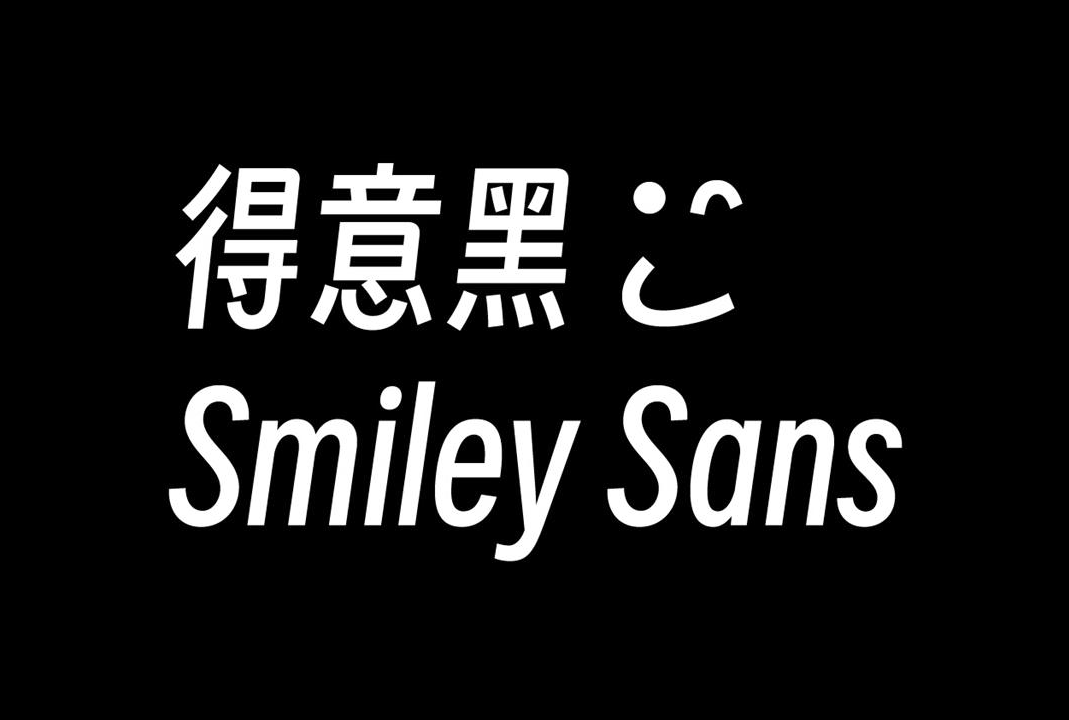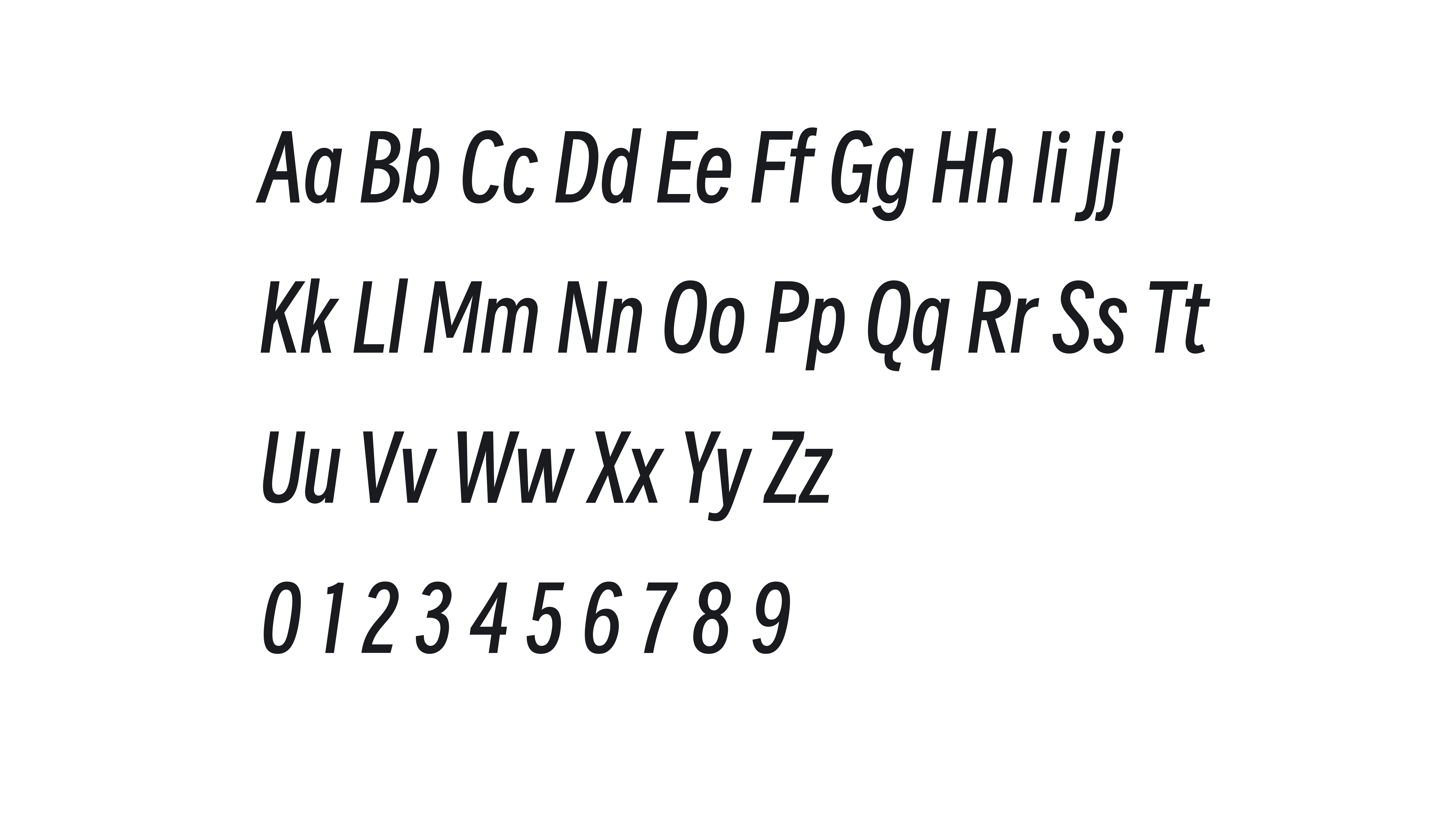
得意黑体(Smiley Sans)是 Bilibili 网友 oooooohmygosh(B站ID:oooooohmygosh)发布的一款开源中文字体,该字体免费商用无任何限制,字体源码一并析出。
得意黑体(Smiley Sans)有三个特征「大弧线、窄、斜」,是一款美术字,该字经过多名字体设计师用时一年多完成。